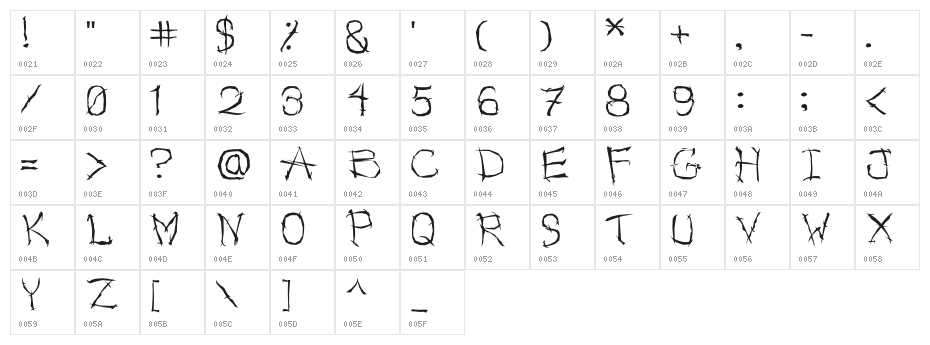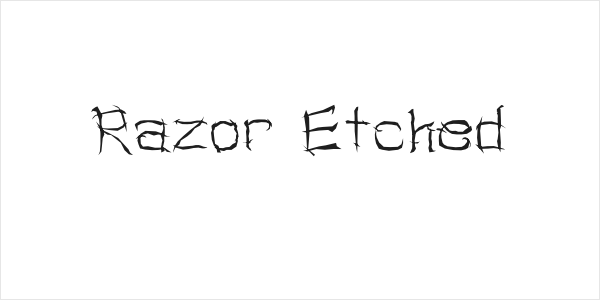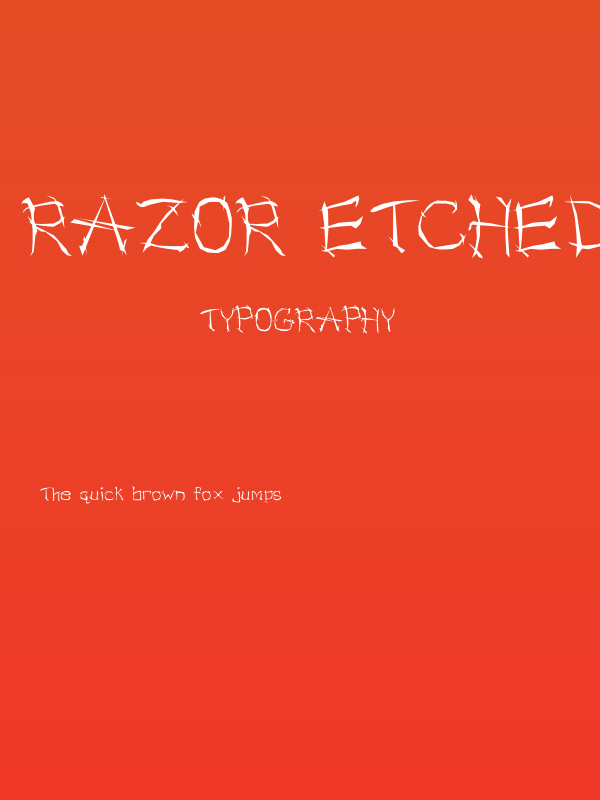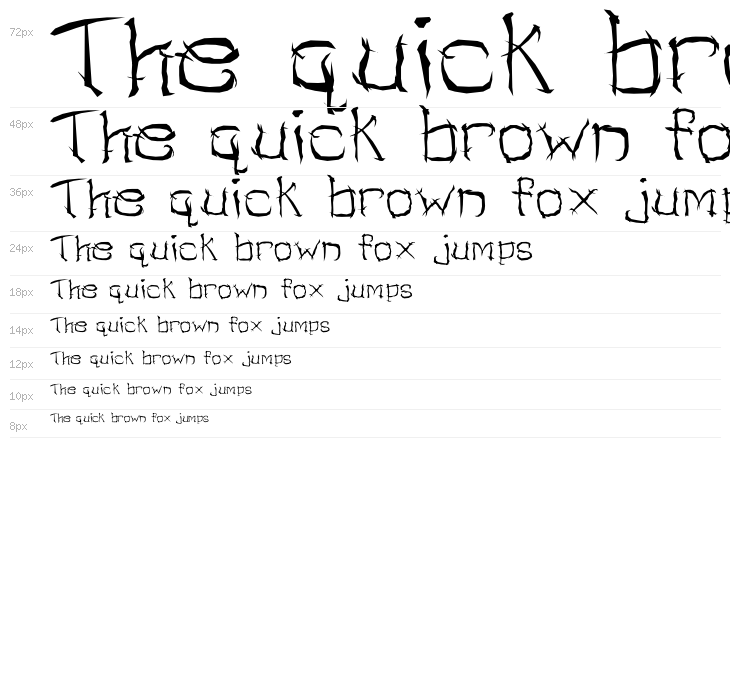
Razor Etched Font
| Caso d'uso | Logos, Headlines |
| Progetti proposti | Ideal for branding, posters, album covers, and any project needing a striking, modern typeface. |